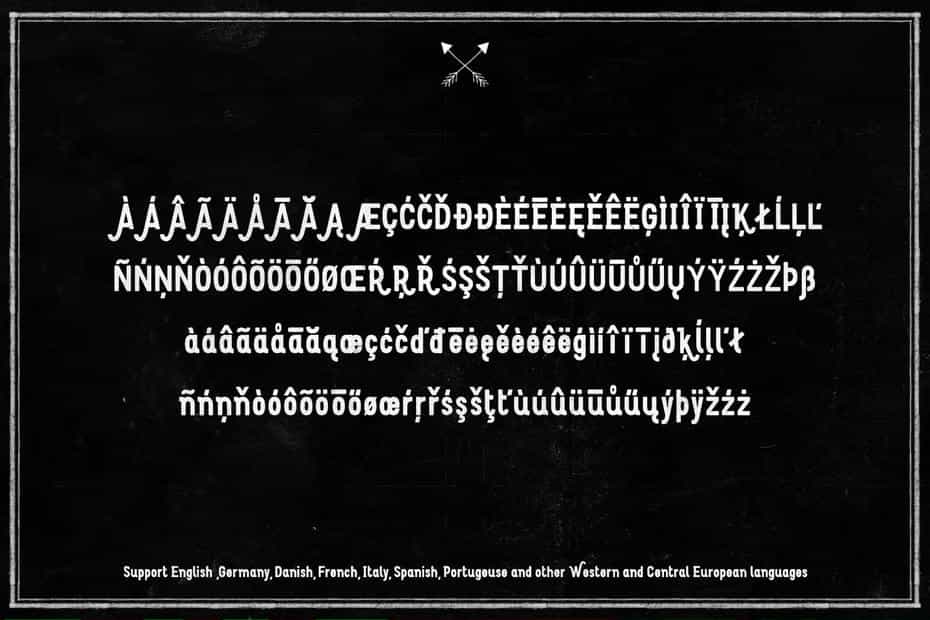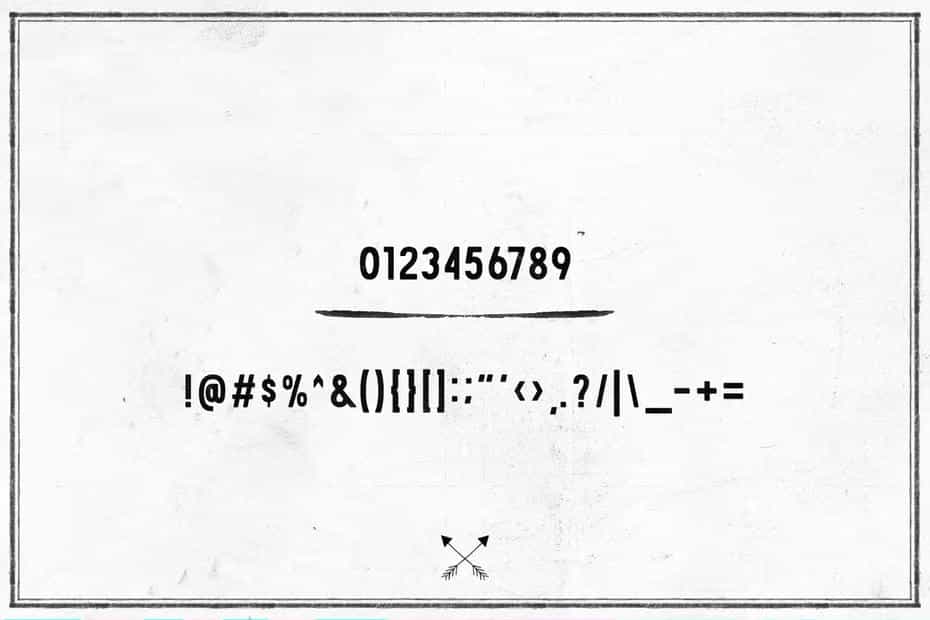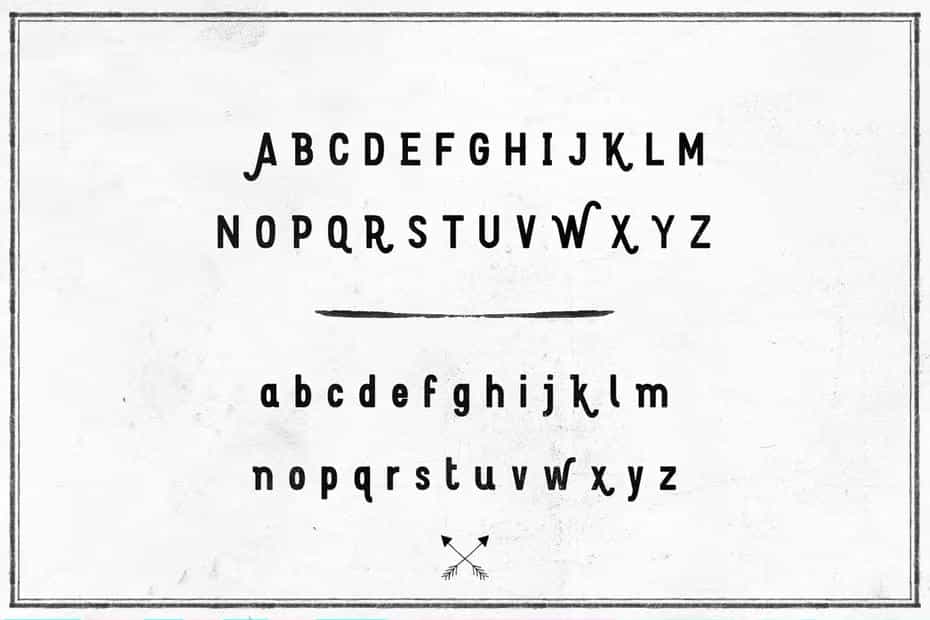
فونت انگلیسی گرافیکی Arson Typeface : این فونت کمی گرد، چند زبانه و دارای المان های وینتیج است که برای لوگو های به سبک وینتیج، برندینگ، هنر، پوستر و … مناسب میباشد.
- عنوان مجموعه: Arson Typeface
- سبک: Sans-Serif
- فضا بین حروف: معمولی
- اندازه بهینه: تمامی سایز ها